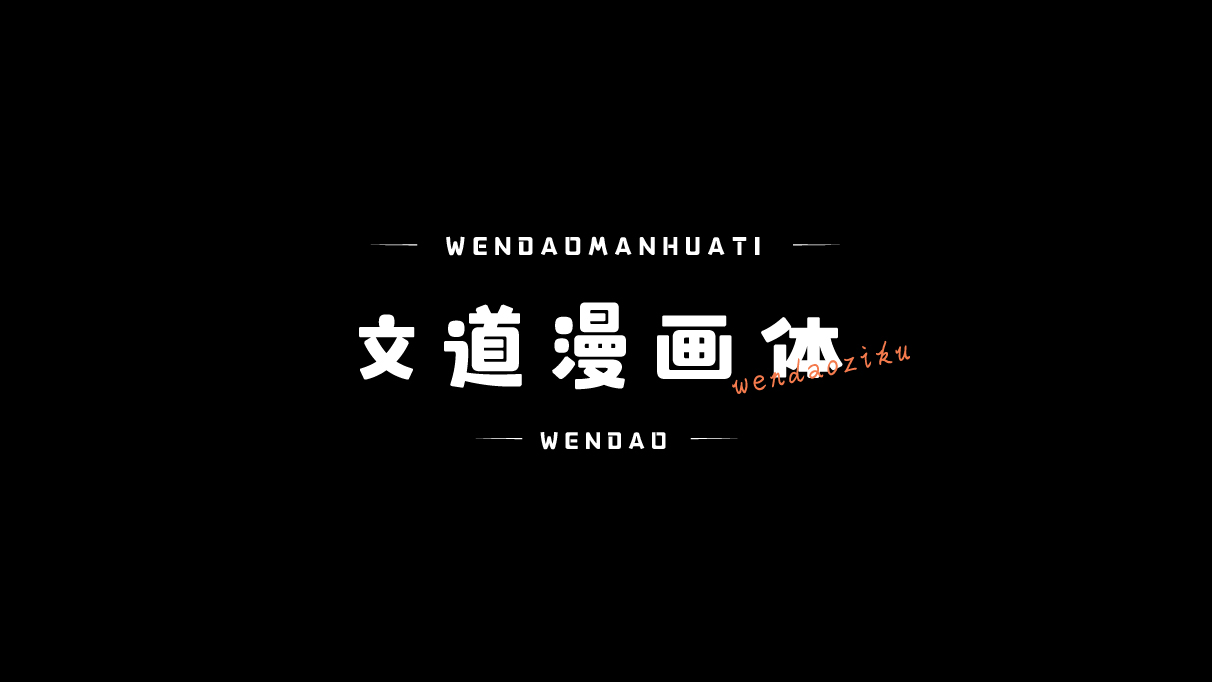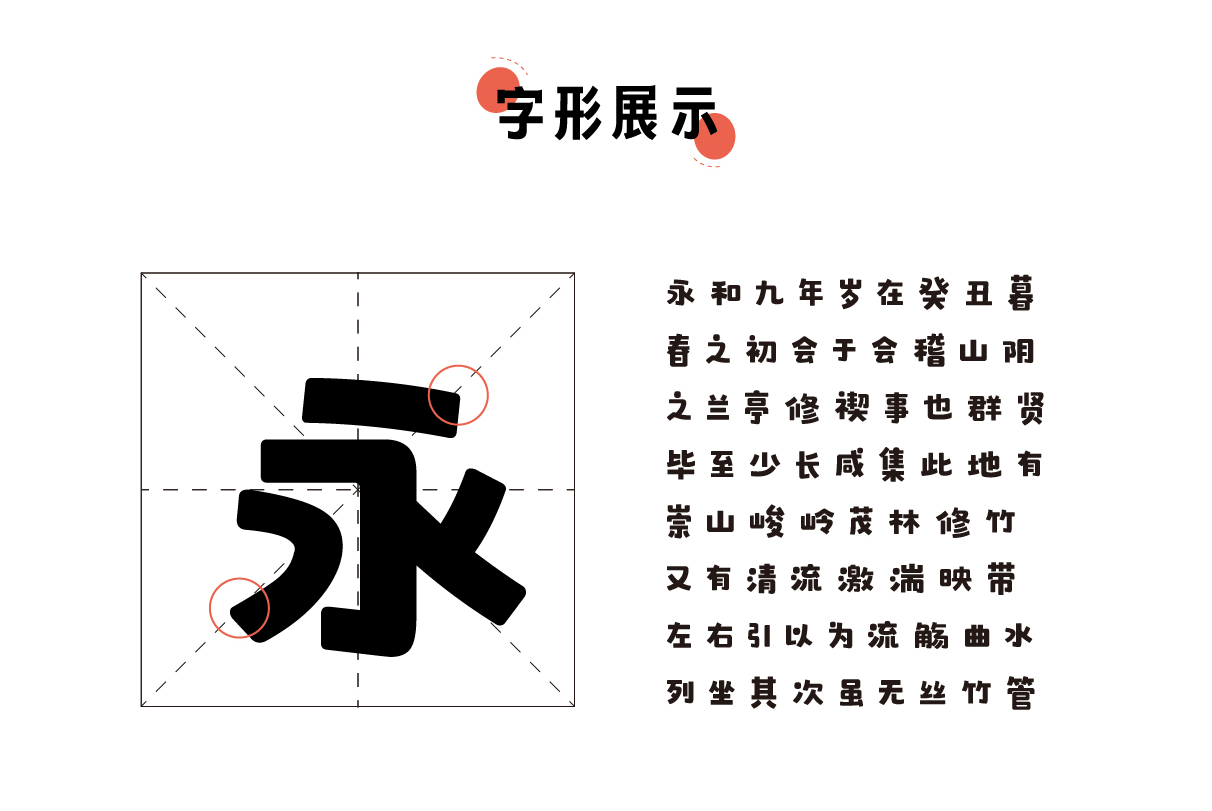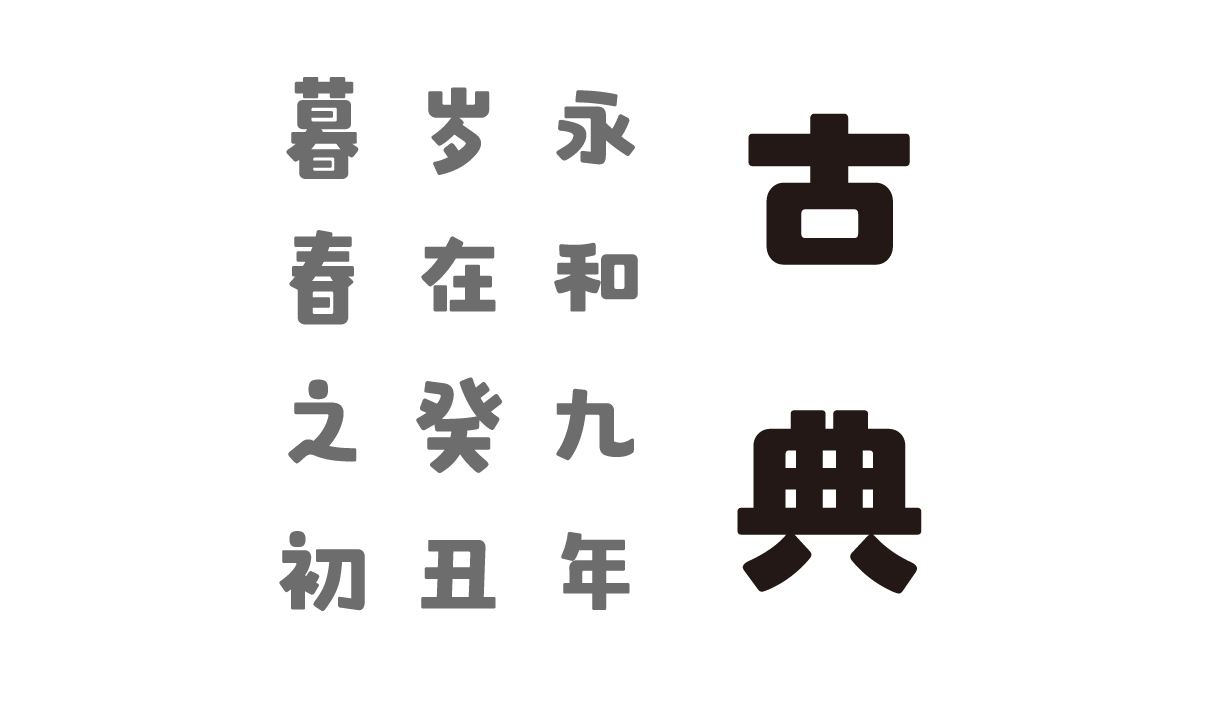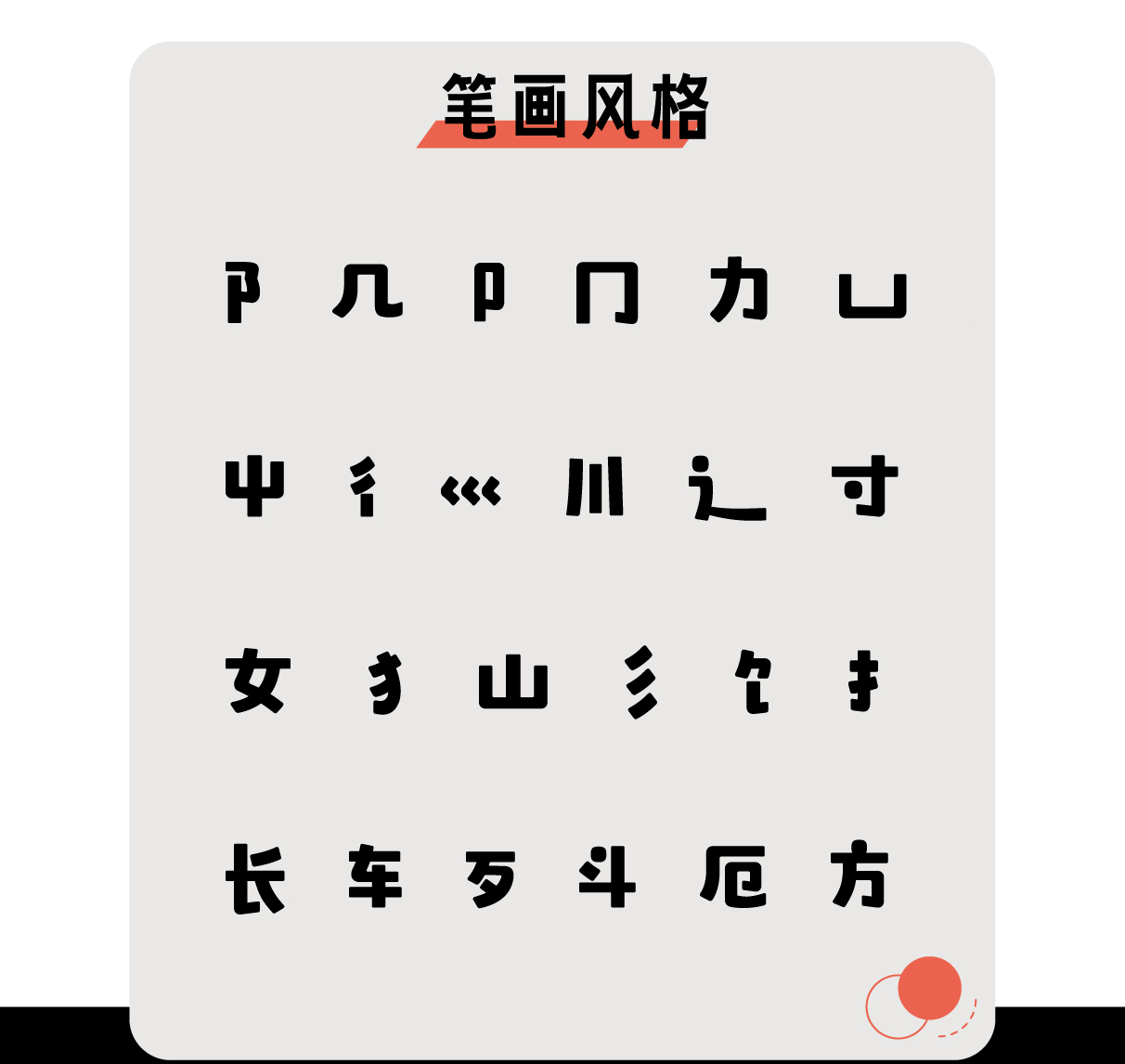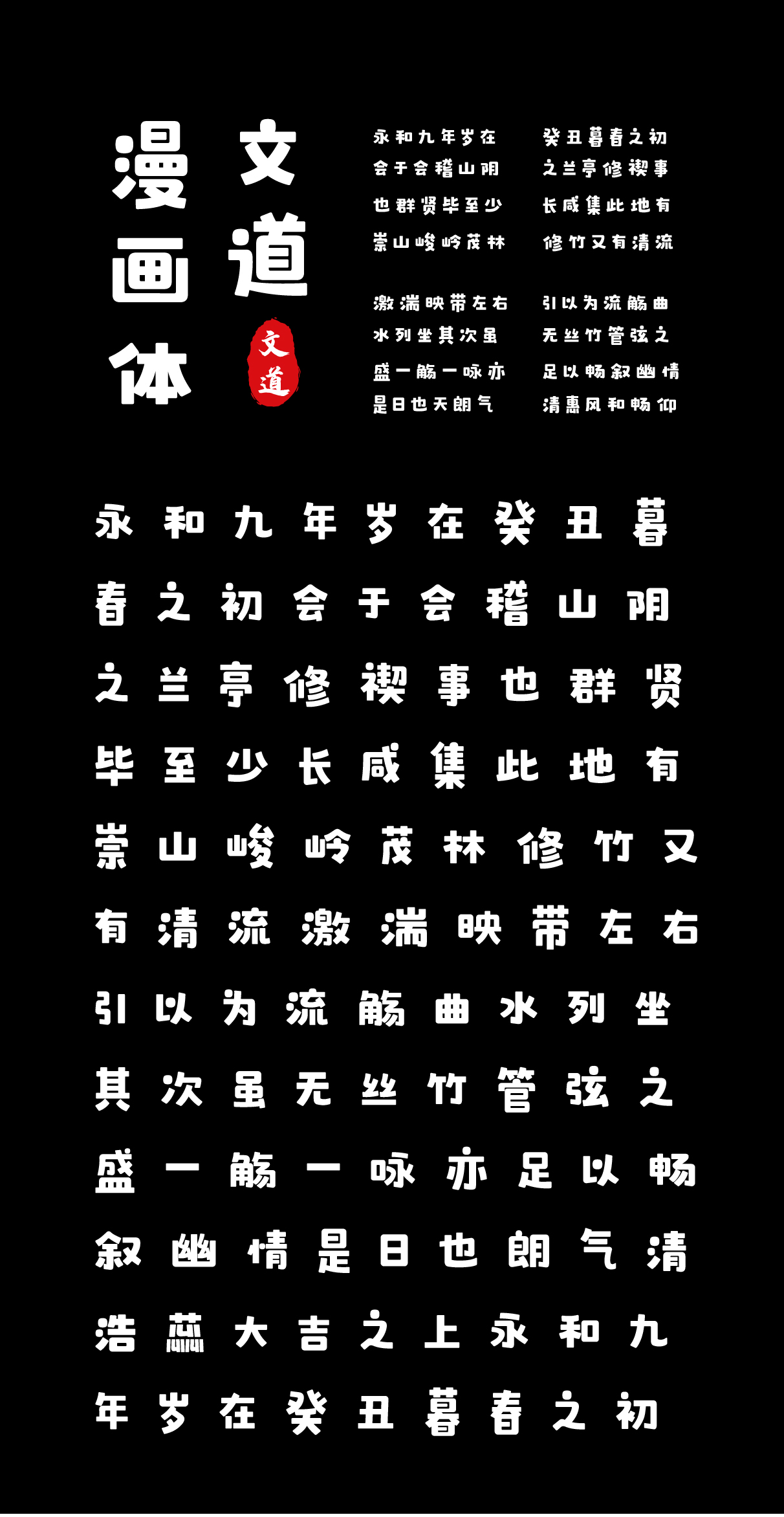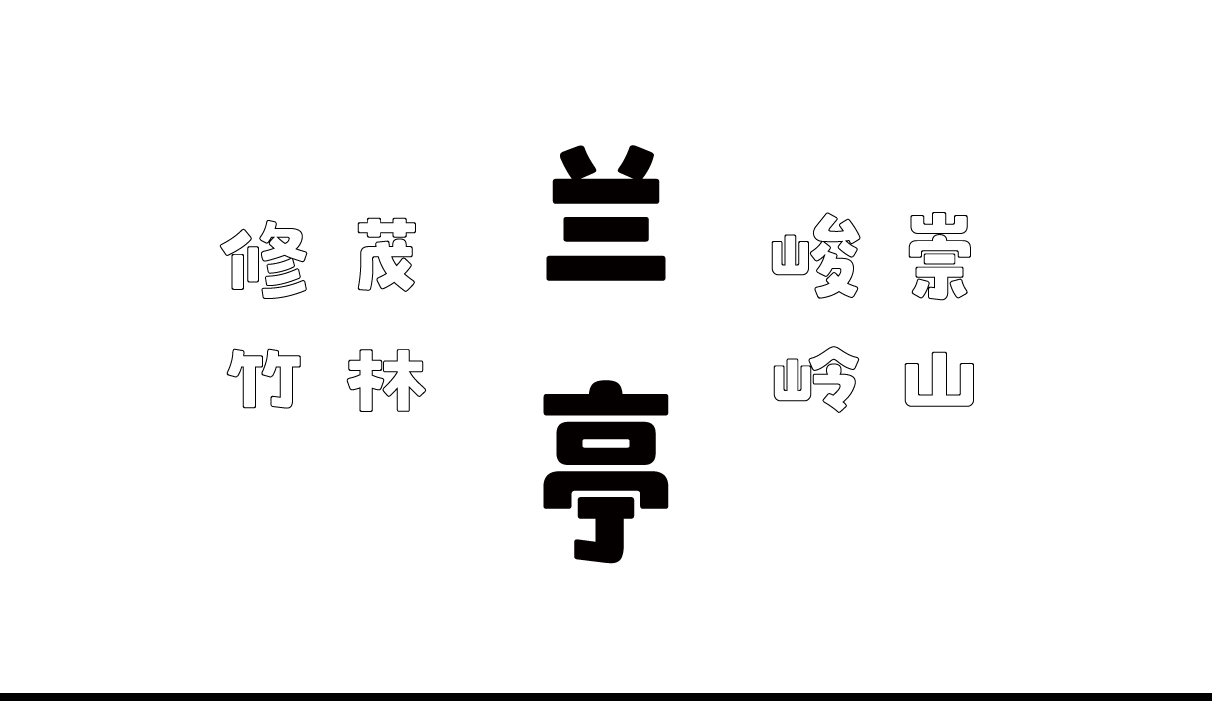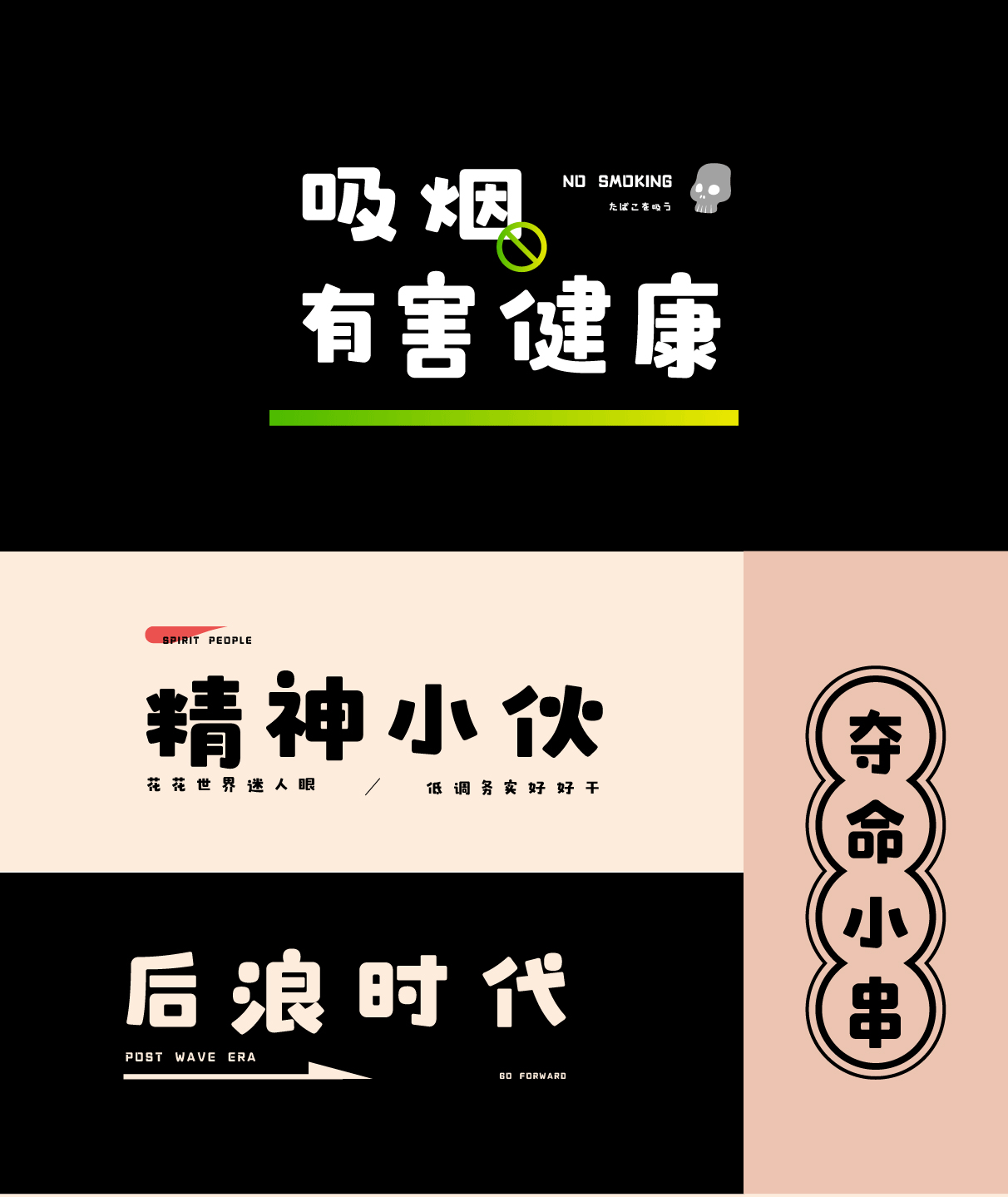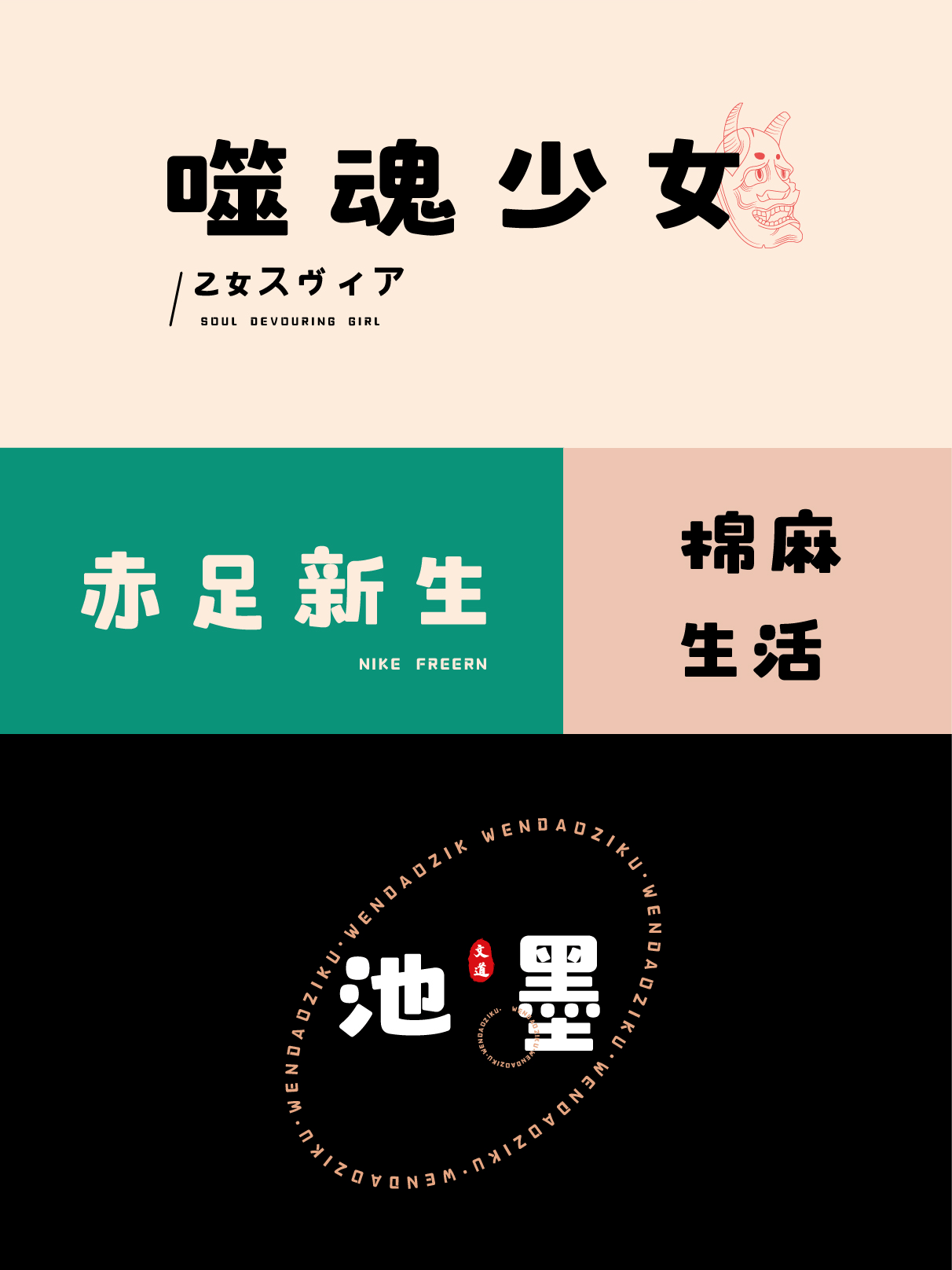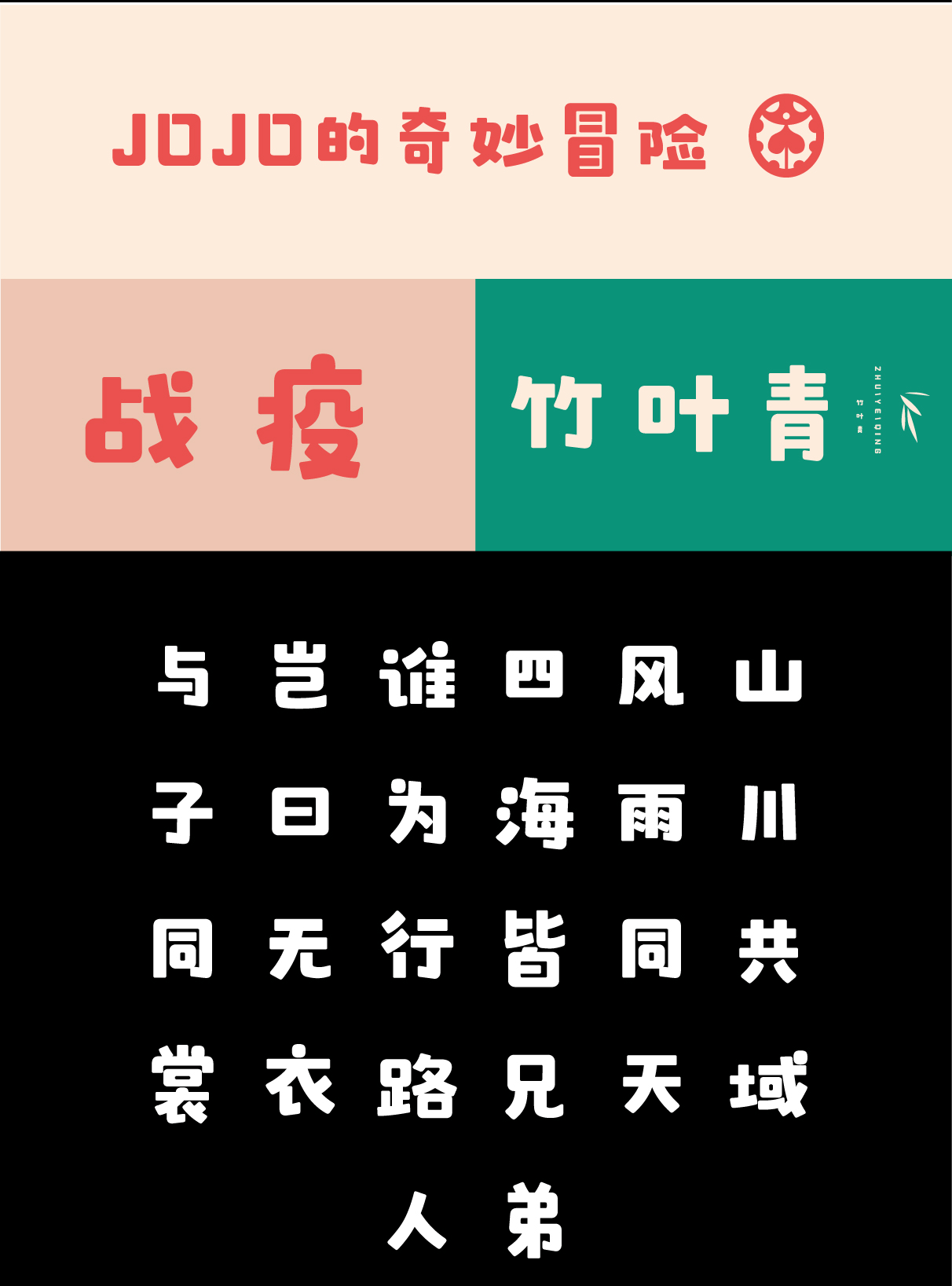
| 字体名称: | 文道漫画体 |
| 简介: | 【文道漫画体】该字体是一款可商用字体,该字粗细均匀,角度略微圆滑,完美呈现出该字在规整又不失一丝趣味。该字包含6763个中文、字母、符号和数字,令人舒适观赏性以及简约风格适合新媒体、电商、海报的标题和logo除了满足传统印刷媒介的标题,还适用于屏幕显示、短视频字幕和产品包装设计。 |